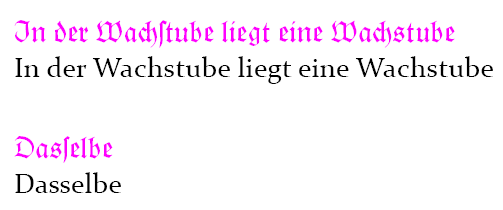
warum sieht die fraktur aus, wie sie aussieht?
Was mich an der Diskussion auffällt ist, daß gebrochene Schriften und damit die Menschen welche sie benutzen und weiterentwickeln, ins konservative Lager gestellt oder gar als tot gesehen werden.
Mir fehlt hier die Toleranz und das Wissen um die Zweischriftigkeit!
Ja ich benutze als erste Schrift die Gebrochene, aber ich benutze auch die Antiqua, auf jedenfalls dort wo ich sie als angebracht sehe und habe kein Problem damit.
Aber ich würde nie auf die Idee kommen, jemand ins politisch rechte Lager zu stellen, nur weil er konsequent die Antiqua benutzt!
Die gebrochene Schrift ist, wie auch die Antiqua, jahrhundertaltes Kulturgut die beide gepflegt gehören. Die einen haben ihre Vorliebe für die oder die andere Schrift, aber beide haben ihre Berechtigung. Gerade von Typographen und Typographinnen sowie an der Typographie Interessierten, erwarte ich das Streben und Verständnis nach der Vielfalt.
Die fehlende Toleranz und der fehlende Wunsch nach Vielfalt ist mir hier als " generelle Forumsmeinung" noch nicht aufgefallen. Eher das Gegenteil.
Du nutzt die gebrochene als erste Schrift? Für deinen privaten Schriftverkehr?
Poms, ich bezog mich nicht »generell auf das Forum«, sondern auf Bemerkung einiger weniger Vorredner.
Ich benutze die gebrochene Schrift durchgängigen als Hauptschrift.
Was mich an der Diskussion auffällt ist, daß gebrochene Schriften und damit die Menschen welche sie benutzen und weiterentwickeln, ins konservative Lager gestellt oder gar als tot gesehen werden.
Das hast du falsch verstanden. Das Forum besteht doch fast auschließlich aus Leuten, die sehr bewusst mit Schrift und Schriftgeschichte umgehen. Und ich kenne hier niemanden, der die Gebrochenen nicht bewahrt sehen möchte. (Und irgendwelche Haltungen/politischen Einstellung will schon gar niemand unterstellen.)
Man kann und sollte aber darüber diskutieren, unter welchen Bedingungen diese Wahrung erfolgen kann. Und dabei geht es vor allem um die »anderen«, die sich nicht so intensiv mit Schrift auseinandersetzen. Was nützt es, wenn eine handvoll Experten diese Schrift benutzen können, aber kein anderer kann sie mehr lesen? Die Zeitungen, die Überschriften in gebrochenen Schriften benutzen, aber auf das lang-s verzichten belegen dieses Dilemma.
Ich sehe da nur drei Möglichkeiten:
a) Die korrekte Schreibung wird wieder in der Schule gelehrt. (Sehr unwahrscheinlich!)
b) Die gebrochenen Schriften werden als tot anerkannt und verschwinden in den Büchern von Historikern und einigen wenigen Schriftexperten.
c) Man lockert die Schreibregeln und kann sie weiterhin verwenden. (Den die jungen Leute lieben die Schrift ja sogar momentan, siehe Hip-Hop-Cover etc.)
Mir wäre c) am Liebsten!
Die Schreibregeln bei der gebrochenen Schriften sind dazu da, die Lesbarkeit zu optimieren, und wenn man sie genau betrachtet, auch nicht schwer zu begreifen da sie in sich Logisch ist.
Gerade die S-Regeln tun bei der Lesbarkeit einen besonderen Dienst. Hier zwei Beispiele:
Das Schluss-s steht immer am Wortende (Wachs-Tube, Das-Selbe), so sind verbundene Wörter die mit S enden leicht zu erkennen, ansonst wird bis auf einige wenige Ausnahmen immer das Lange-s gesetzt. Das Eszett bleibt davon unberührt.
Ach so, ich dachte nur von wegen Punkt A: „Die korrekte Schreibung wird wieder in der Schule gelehrt“.
Aber ander Frage:
Die Zeitungen, die Überschriften in gebrochenen Schriften benutzen, aber auf das lang-s verzichten belegen dieses Dilemma.
So viele Zeitungen kenne ich nicht... kannst Du mir da welche nennen, die bei der Überschrift auf das Lange-s verzichten?
Ich benutze die gebrochene Schrift durchgängigen als Hauptschrift.
darf ich mal fragen was du genau machst? bist du grafiker und nutzt die schriften 'als eigenen stil' in deinen werken oder ist schrift eher nur ein
hobby für dich und du benutzt sie in deinen persönlichem schreibverkehr?
Ich habe konservativ zunächst keineswegs im Sinne von politisch rechts verstanden. Ich glaube aber, dass Entwicklung etwas positives ist und diese nun einmal verlangt, dass neue Dinge Bestehendes verdrängen.
Leute als faul zu bezeichnen, weil Sie keine gebrochene Schriften lesen können, finde ich etwas … da fehlen mir eigentlich die Worte — schräg, vielleicht.
Ich finde es durchaus als Bereicherung, wenn es jetzt zu einer Renaissance der Gebrochenen kommt. Ich glaube aber auch, dass die Gebrochene durchaus davon profitiert, wenn man ihr zugesteht nach den aktuell bestehenden Schreib- und Satzregeln angewendet zu werden.
Das festhalten an Ligaturen oder einem langen ſ weil es eine Funktion erfüllen mag, halte ich dennoch für etwas ›engsichtig‹. Es fokussiert auf ein Detail, welches vielleicht in der Tat mangelhaft sein mag, allerdings in einem System das durchgängig mangelhaft ist. Man muss nur mal geschriebenen Text 1:1 nach den Buchstabenlauten lesen, dann hat das Ergebnis nur mehr wenig damit zu tun was mit den Buchstaben kodiert wurde.
Das ist so eine Behauptung, die man nur beim »Bund für deutsche Schrift« oder in missionarischen Fraktur-Publikationen findet. Sie widerspricht aller meiner Erfahrung sowie dem Großteil der Literatur zur Lesbarkeit. – Und ich sage dies notabene als ein Liebhaber der Frakturschriften …